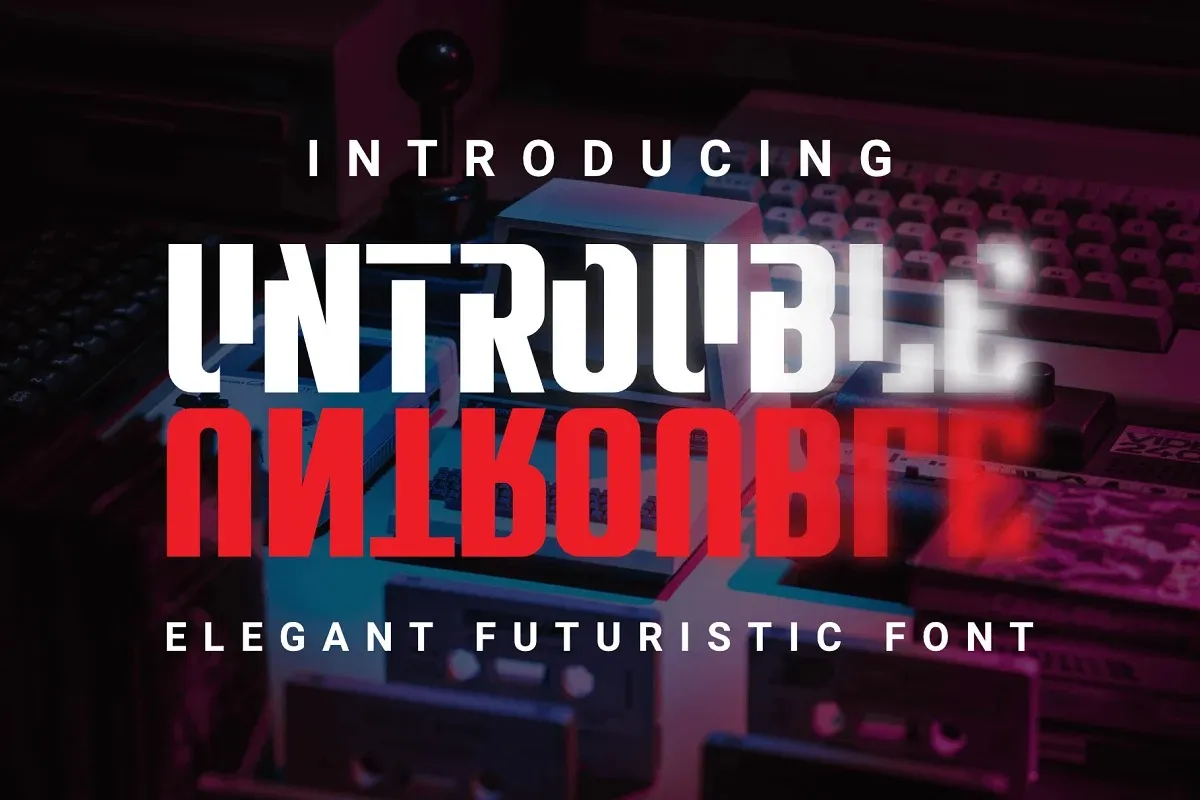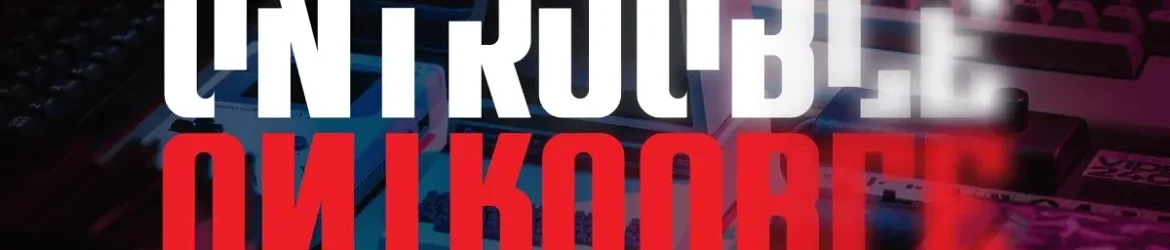
Untrouble Font – Download Grátis
A Untrouble Font é uma escolha perfeita para quem deseja incorporar um design minimalista e moderno em seus projetos digitais. Inspirada nos clássicos do marketing visual, como a billboards e as marcas de lojas dos anos 80, esta fonte sans-serif com letras maiúsculas reúne todas as características necessárias para adaptar-se perfeitamente às mais diversas aplicações. Ideal tanto para design gráfico quanto para os ambientes virtuais de jogos e redes sociais, a Untrouble também atende aos anseios do branding e da publicidade. Suas linhas elegantes são ótimas opção para as etiquetas de produtos ou até mesmo para o design dos materiais promocionais, como flyers e banners. Com um estilo que transmite simplicidade e eficiência, a Untrouble é uma excelente opção para criar mensagens impactantes em qualquer projeto. A sua versatilidade faz da fonte uma escolha irresistível para designers de todos os níveis.